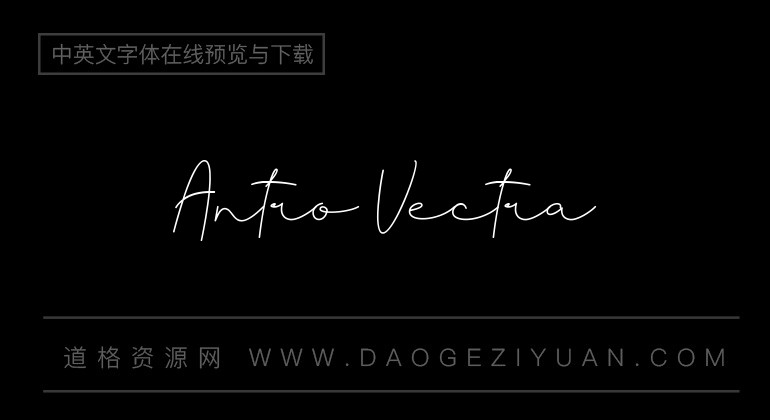
Antro Vectra
Antro Vectra 是一款由著名设计师马克·莫里斯(Mark Morris)设计的英文字体。它是一款类似于线条风格的字体,具有流畅的线条和清晰的字形,可以给文字带来独特的外观和感觉。Antro Vectra 具有几种不同的字体风格,可以满足不同的设计需求。它可以用于创建商标、标题、标语等,有助于增强文字的视觉效果。
Antro Vectra是一款非常不错的手写艺术字体,具有很好的视觉感,适合于文化类的宣传设计、商业类品牌的广告和产品包装设计以及个性化文字排版等较多场景。